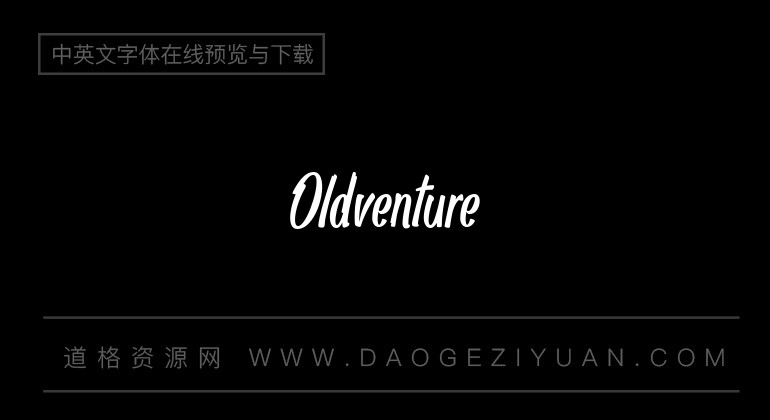
Oldventure 是一款由 Fontfabric 制作的漂亮的手写字体。它具有轻松、温暖、抒情的外观,能够带给您独特的视觉体验。它的字体特点是细节丰富,可以为您的设计提供精美的装饰效果,极具视觉冲击力。它可以用于各种不同类型的设计,从简单的标题到复杂的海报,都能让您的设计更加精致。内容介绍
Oldventure是一款非常不错的手写艺术字体,具有很好的视觉感,适合于文化类的宣传设计、商业类品牌的广告和产品包装设计以及个性化文字排版等较多场景。